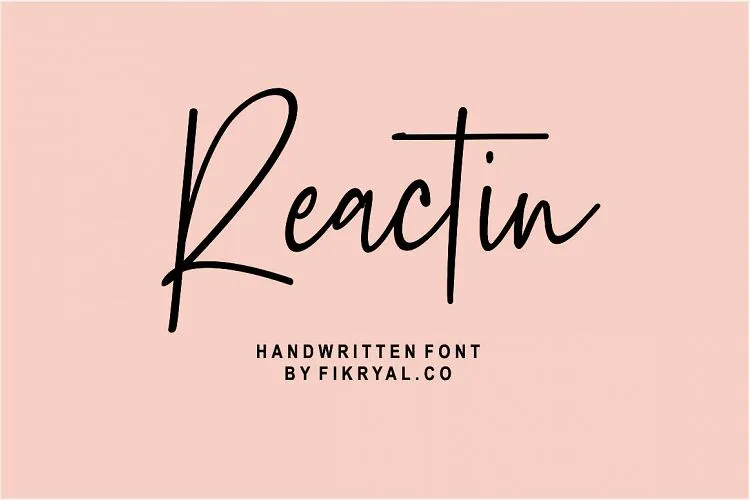
Reactin Signature Font – Download Grátis
Olá, amigos. O “Reactin Font” é uma fonte script com estilo de escrita manuscrita que adquirem um carácter atraente, divertido e descontraído. Este tipo de letra é extremamente versátil e perfeito para qualquer projeto. Desenvolvido e compartilhado por Teuku Risky Firmina, esse é uma nova fonte moderna e estilizada escrita à mão. Perfeita tanto para logomarcas e embalagens, como para anúncios e design de produtos, este tipo de letra adquirem um tom elegante que se adequa a vários cenários. Seja em postes de redes sociais, em embalagens de produtos ou até mesmo nos rótulos das caixas, o “Reactin Font” é uma opção ideal para qualquer projeto em que você deseje transmitir modernidade e estilo.